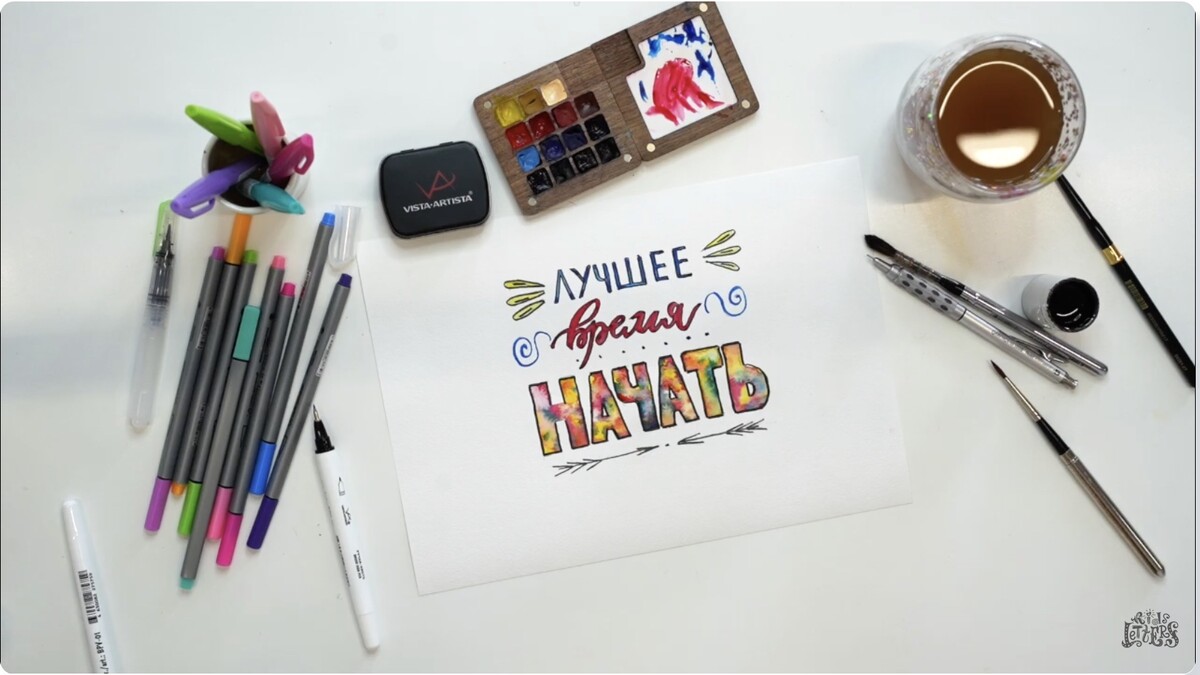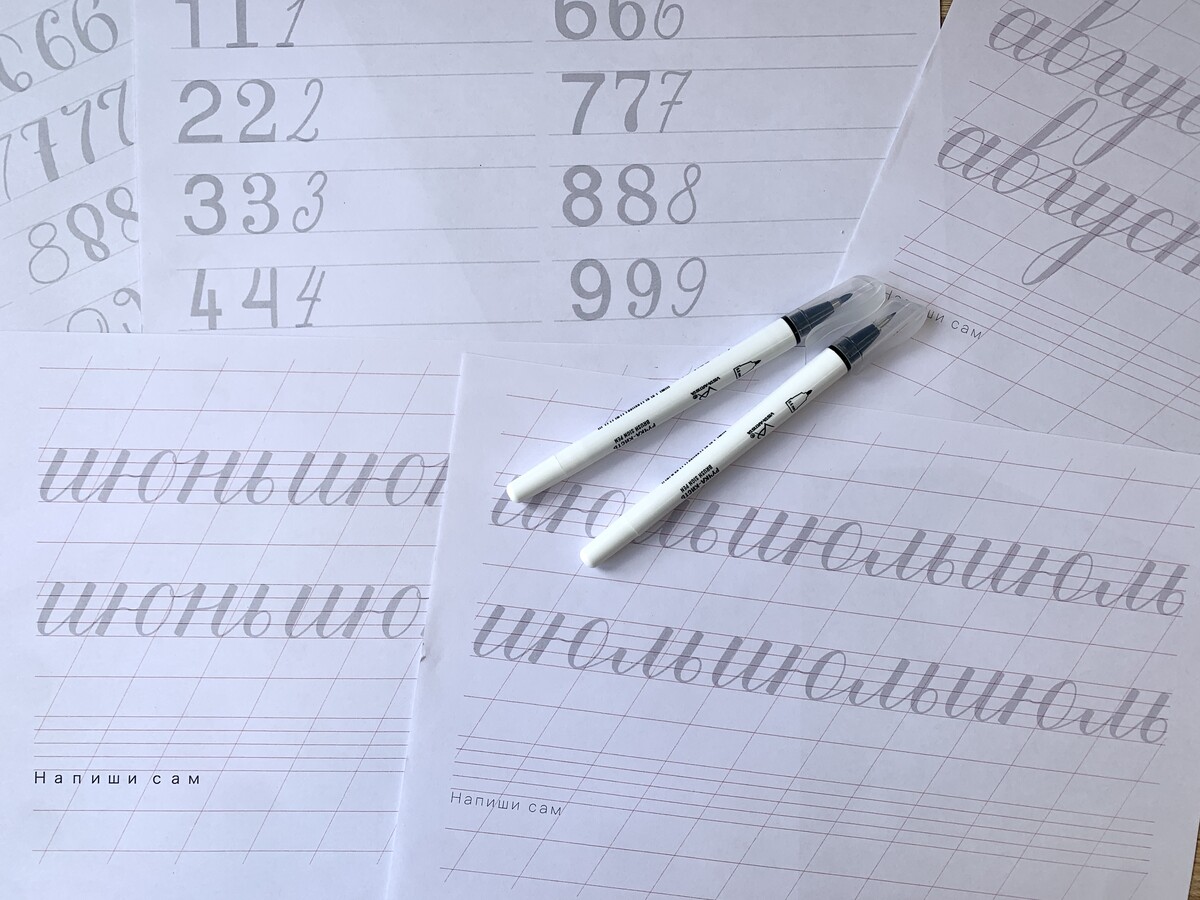
Онлайн-курс «Письмо кистью» для педагогов
Освойте метод развития почерка у детей и получите практический инструмент для занятий в классе и дома
Сегодня в школах не учат письму.
Дети теряют навык красивого почерка, а педагоги и родители остаются один на один с этой проблемой.
Прописи больше не работают.
Они дают технику, но не формируют любовь и вовлечённость. Дети устают, зажимают руку, пишут медленно и неровно.
Решение — письмо кистью как метод в педагогической практике.
Крупные движения снимают мышечное напряжение у детей,
форма буквы становится наглядной,
ребёнку легче освоить ритм и структуру письма.
Сначала — работа кистью, затем — плавный и осознанный переход к школьному письму.
Почему это важно?
ПРОГРАММА КУРСА
что внутри курса?
0
Вводная часть
- Как будет проходить обучение
- Знакомство с инструментами: кисть, брашпен
- Посадка и постановка руки
1
Базовые элементы, конструктор и группы букв
- Знакомство с инструментами: кисть, брашпен
- Посадка и постановка руки
- Первые линии, каллиграфический ритм, «ручка зонтика», овалы, полуовалы
2
Строчные буквы
- Строчные буквы русского алфавита от «а» до «я»
- Алгоритм написания, включая мягкий и твёрдый знак
- Соединение элементов в букве
3
Заглавные буквы
- Все заглавные буквы алфавита
- Соединение букв в слова
- Плавность, ритм и читаемость надписей
4
Соединения и слова
- Соединение
- Итоги базовой части обучения
- Закрепление навыков
5
Творческая часть. Ритм. Композиция. Цвет
- Ритм как ключ к красивым буквам
- Нарушение правил: вариация высоты, отказ от наклона, игра с нажимом
- Сочетание элементов в словах и фразах
6
Итоговая работа
- Итоговая работа
Итоги и дальнейший путь мастера
Что вы получите от курса?
👩🏫 Для педагога:
1. Получаете готовую методику для работы с письмом в классе, на дополнительных занятиях и индивидуально.
2. Осваиваете письмо кистью на практике и можете уверенно показывать его детям.
3. Расширяете инструментарий для повышения вовлечённости учеников без перегрузки и «скучных прописей».
4. Добавляете в свою профессиональную практику творческий формат, который поддерживает интерес детей и снижает выгорание у педагога.
👧 Для учеников:
1. Осваивают плавное и аккуратное письмо кистью как подготовку к школьному письму.
2. Снижается напряжение в руке, улучшается координация и ритм движений.
3. Повышается интерес к занятиям письмом за счёт творческого формата.
4. Формируется более уверенное и осознанное движение руки при письме.